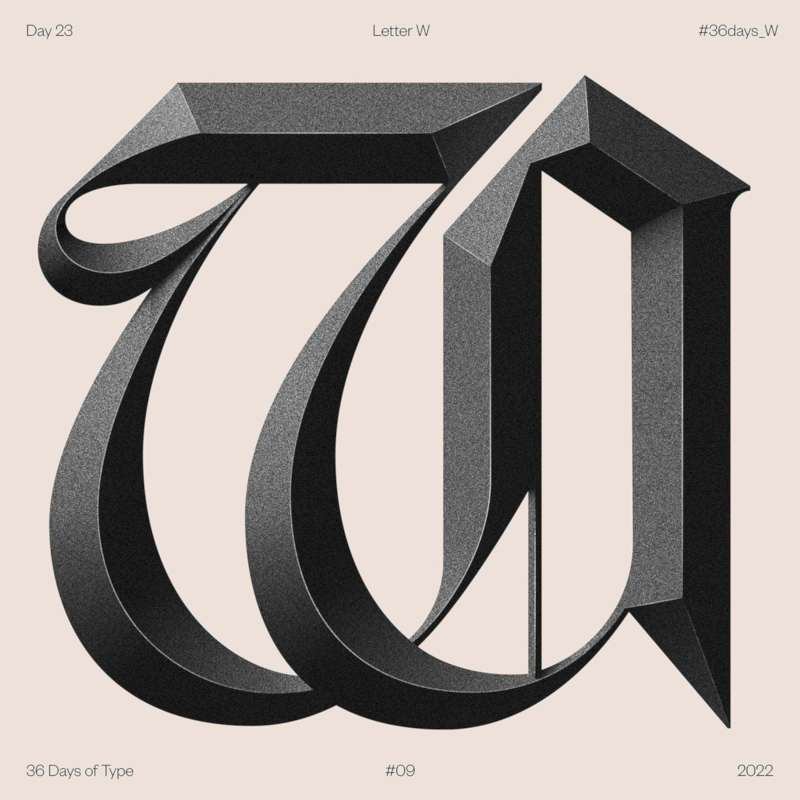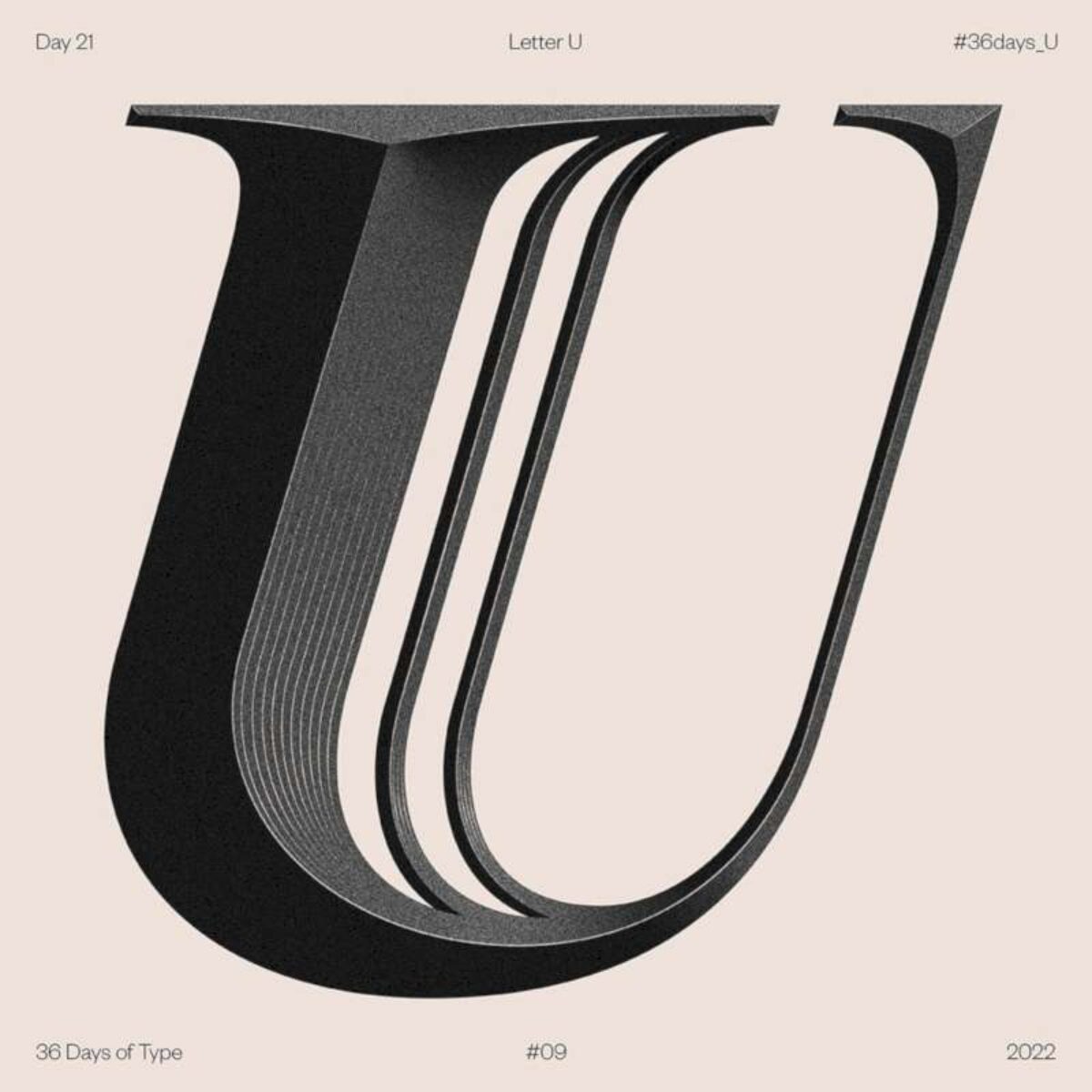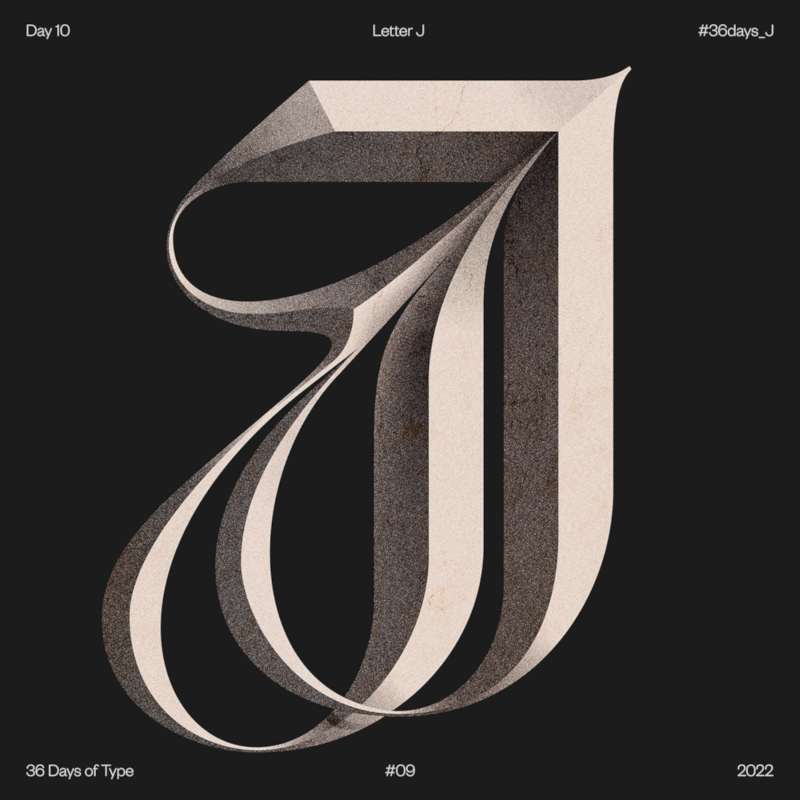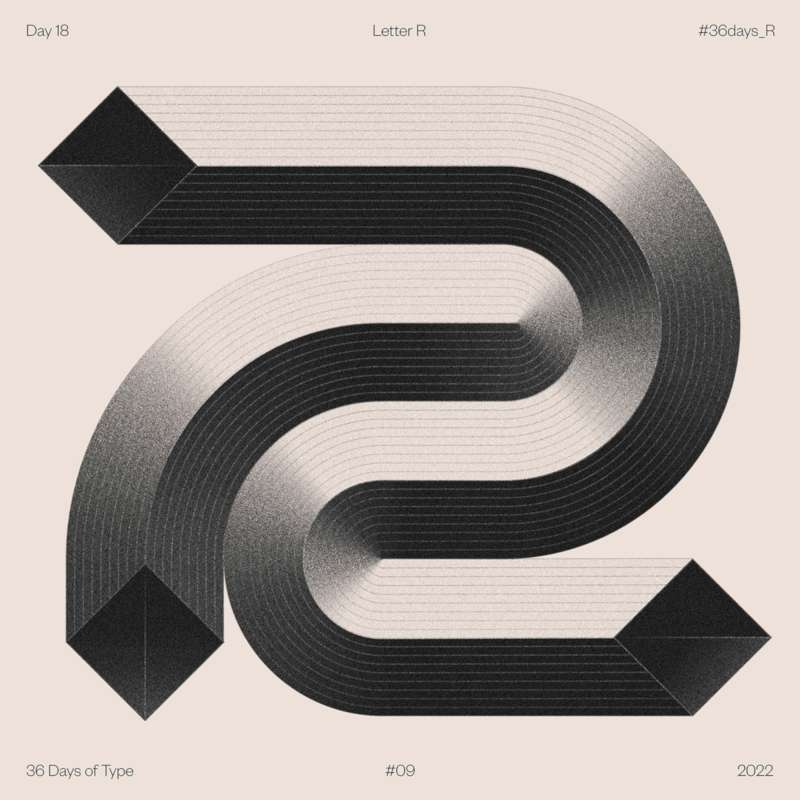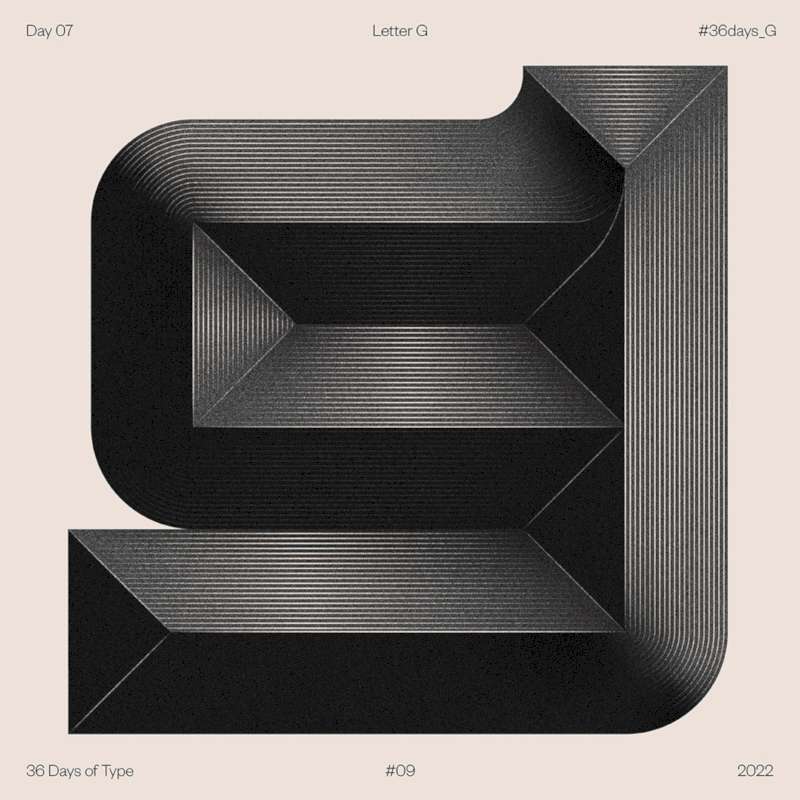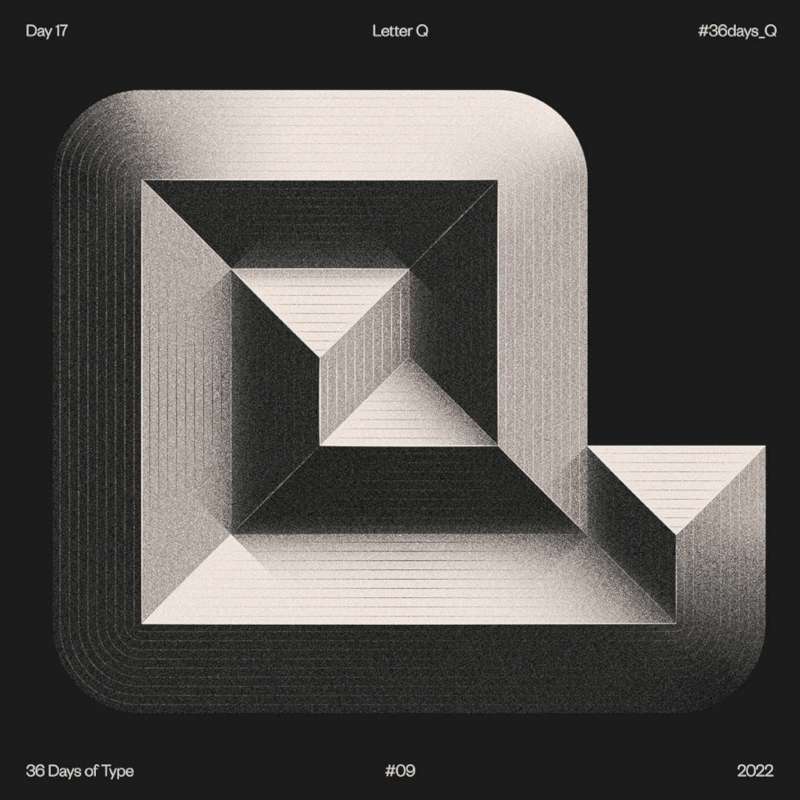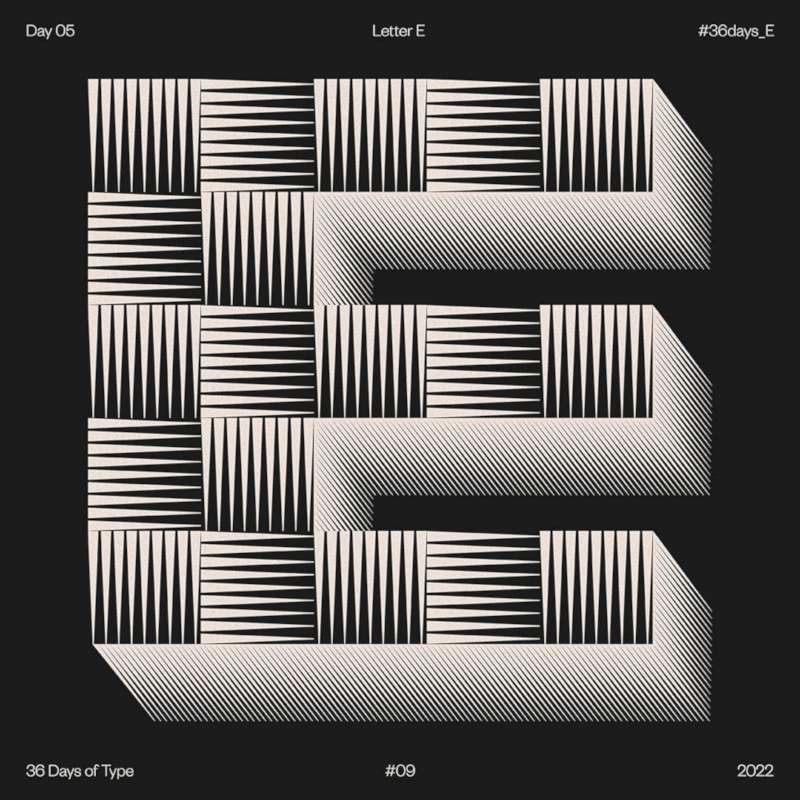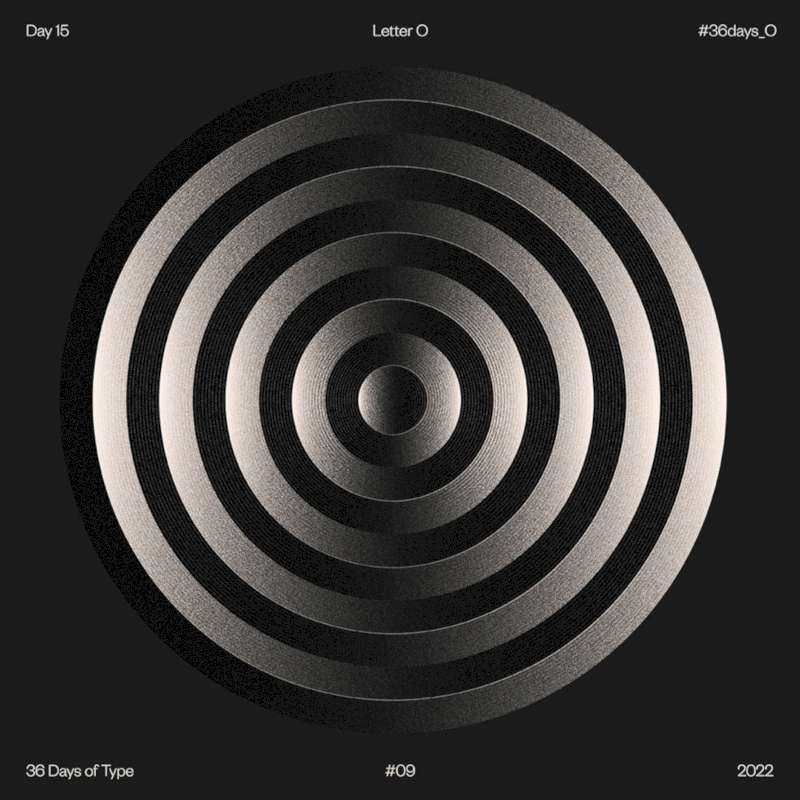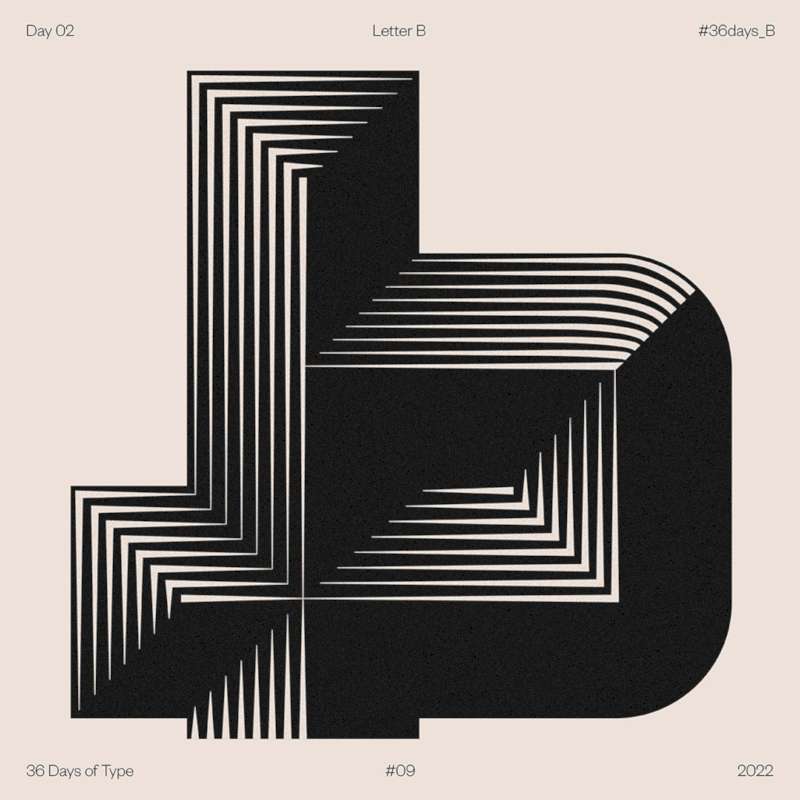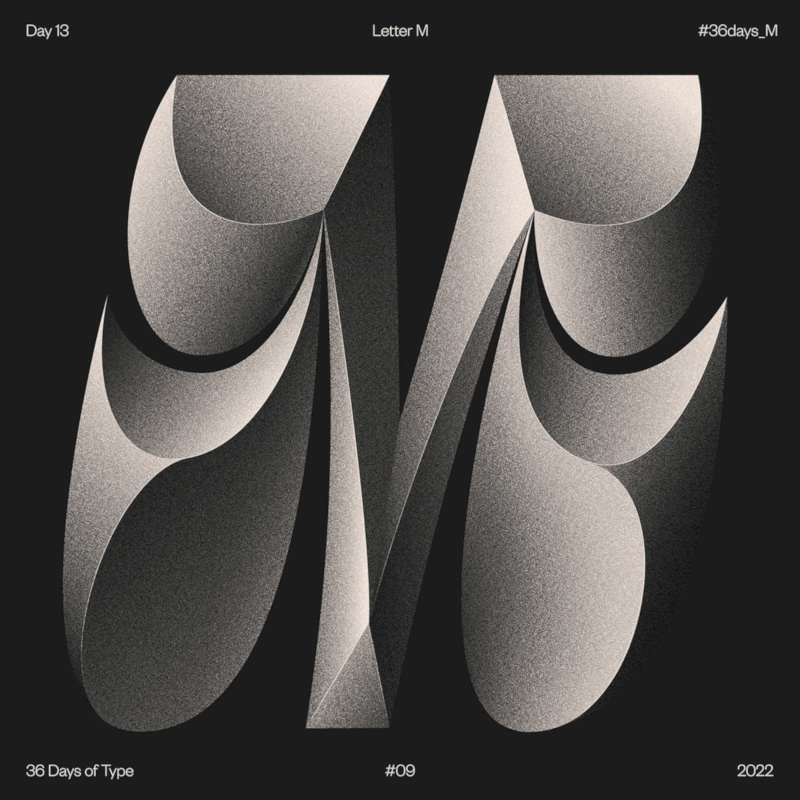
A Magnificência Monocromática de Alisa Burzic
Alisa Burzic é uma designer gráfica cuja carreira começou com a pintura. Hoje em dia, direto de Belgrado, a capital da Sérvia, ela explora os limites visuais da tipografia de um jeito bem monocromático.
Sua carreira como designer começou de um jeito diferente do comum já que ela não estudou design gráfico. Ela acabou graduando em Pintura na Academia de Arte de Belgrado e lá ela aprendeu técnicas tradicionais de pintura. E foi esse conhecimento que levou Alisa Burzic ao campo do design gráfico.
Para ela, uma escola de design não é necessária como precursor necessário para uma carreira. Para Alisa Burzic, o necessário é ter curiosidade e compromisso e isso você pode aprender fora do sistema educacional.
Conheci o trabalho de Alisa Burzic enquanto navegava sem direção no Instagram há alguns dias. Seu trabalho de tipografia monocromática chamou minha atenção devido a suas formas experimentais e como que ela trata das imagens de um jeito quase vintage.
Abaixo, acabei selecionando algumas das letras mais interessantes que ela publicou no seu Behance com o nome de 36 Days of Type 2022 Edition. Dá para ver ainda mais exemplos tipográficos no link abaixo.